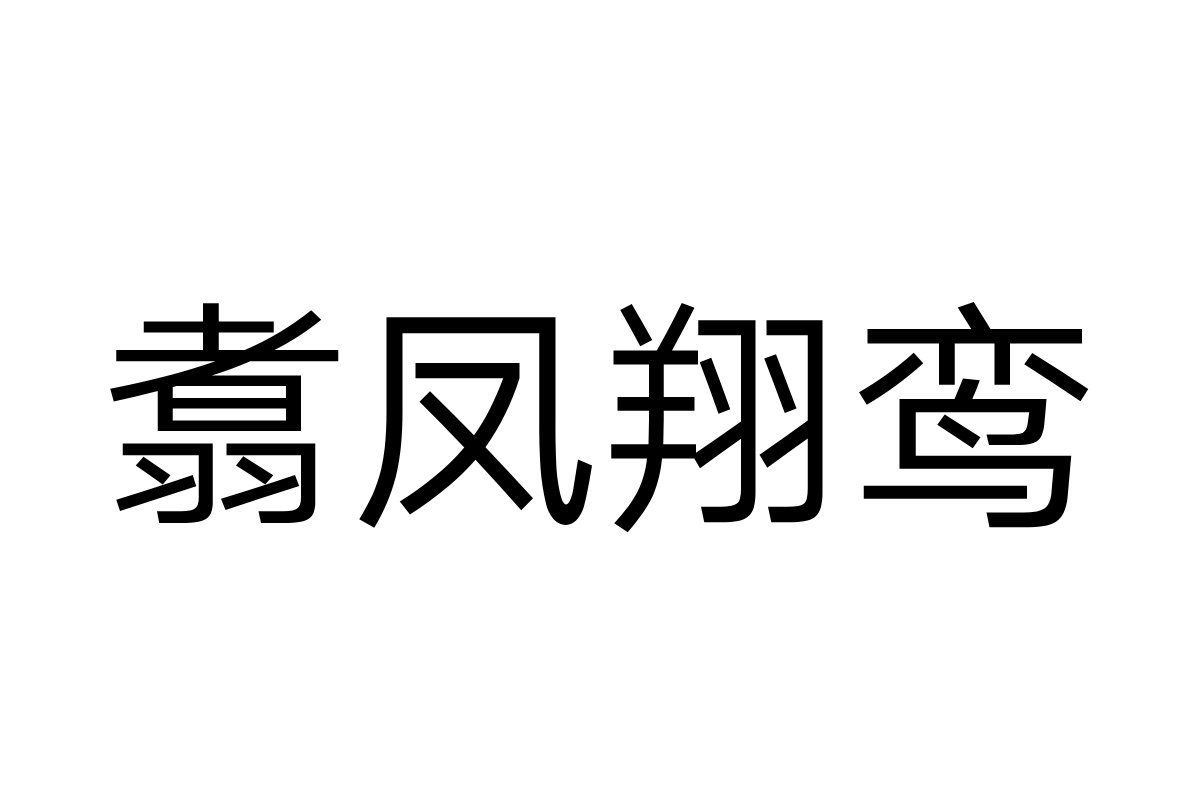
汉仪旗黑-50是一款现代感十足的中文字体,由汉仪公司设计。这款字体以其简洁、大气的设计风格而受到广泛欢迎。它具有以下特点:
1. 字形结构:汉仪旗黑-50采用了简洁的字形结构,笔画流畅,易于阅读。它适用于各种标题、正文和广告等场合。
2. 风格特点:这款字体具有现代感和科技感,适合用于科技、互联网、电子等领域的标识和宣传材料。同时,它也适合用于时尚、艺术、文化等领域的宣传和展示。
3. 适用范围:汉仪旗黑-50适用于各种印刷和数字媒体,包括书籍、杂志、报纸、广告、网站、APP等。
总之,汉仪旗黑-50是一款简约、现代的中文字体,适用于各种场合和领域,深受设计师和用户的喜爱。